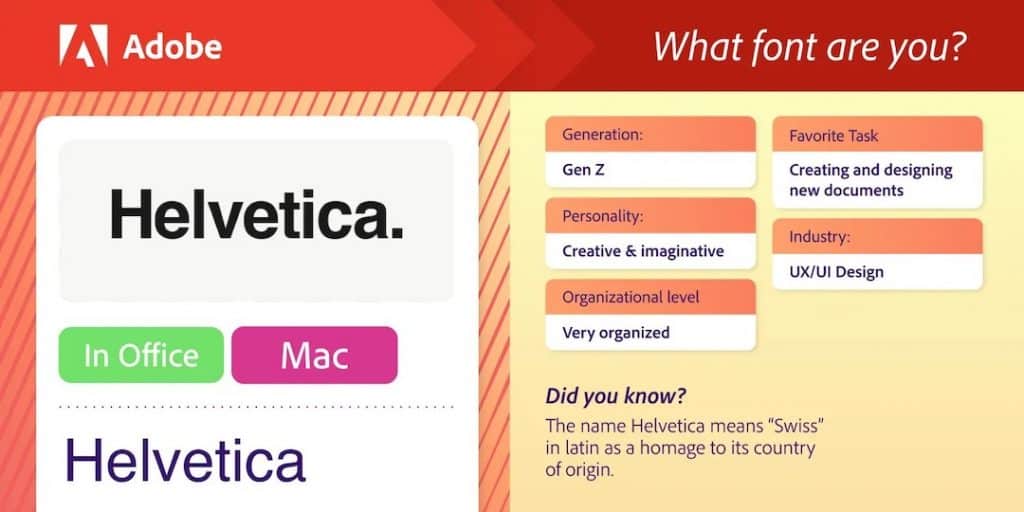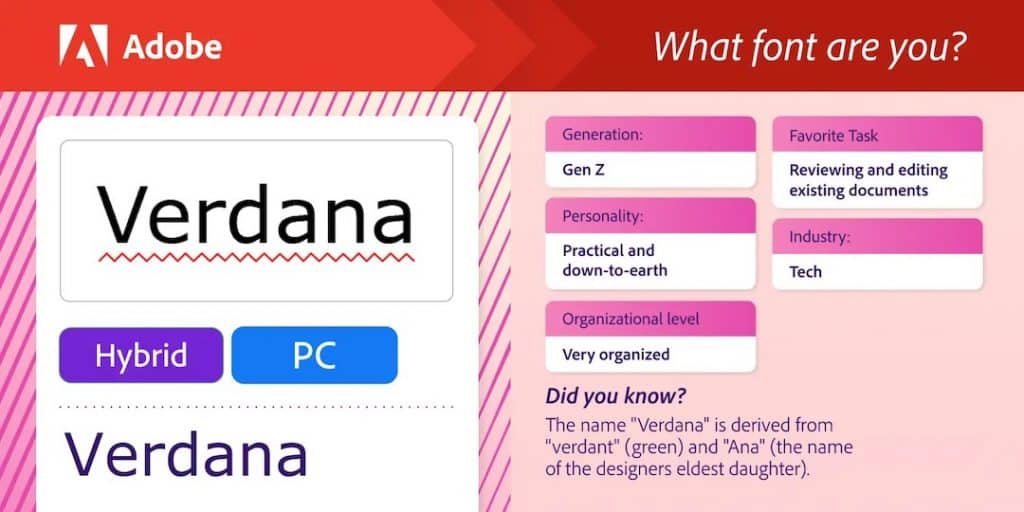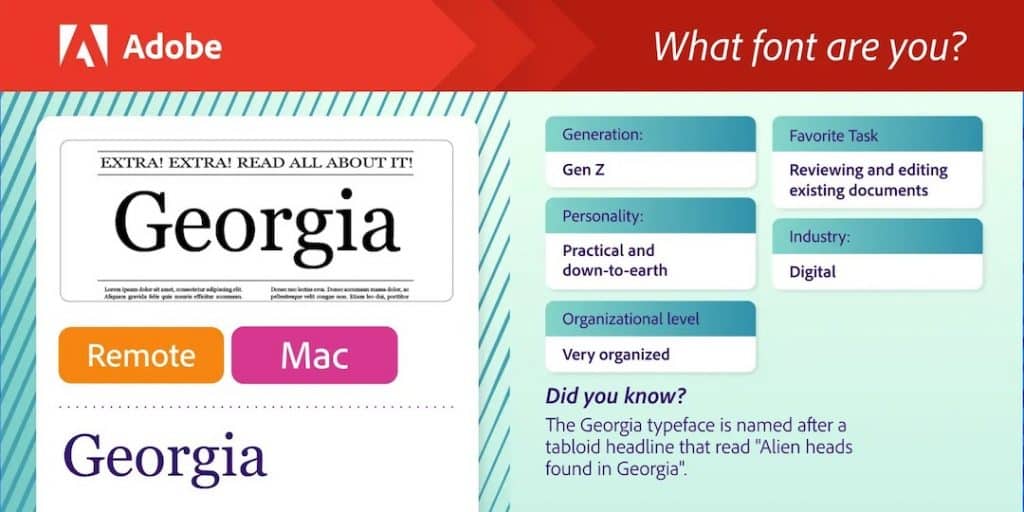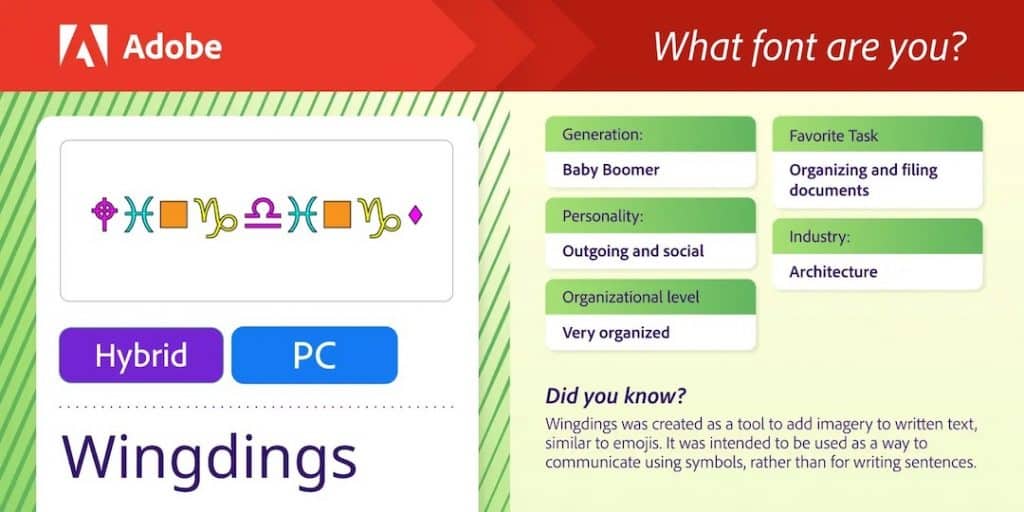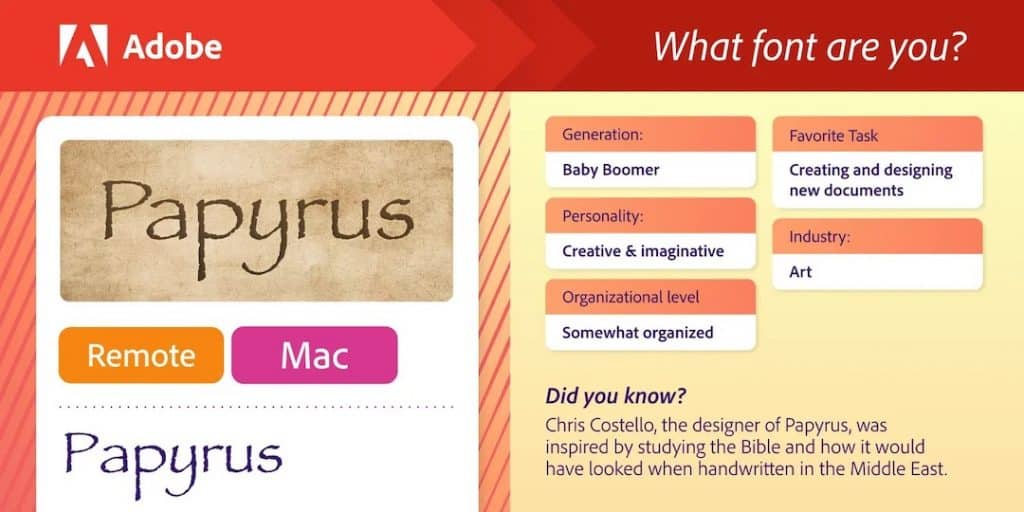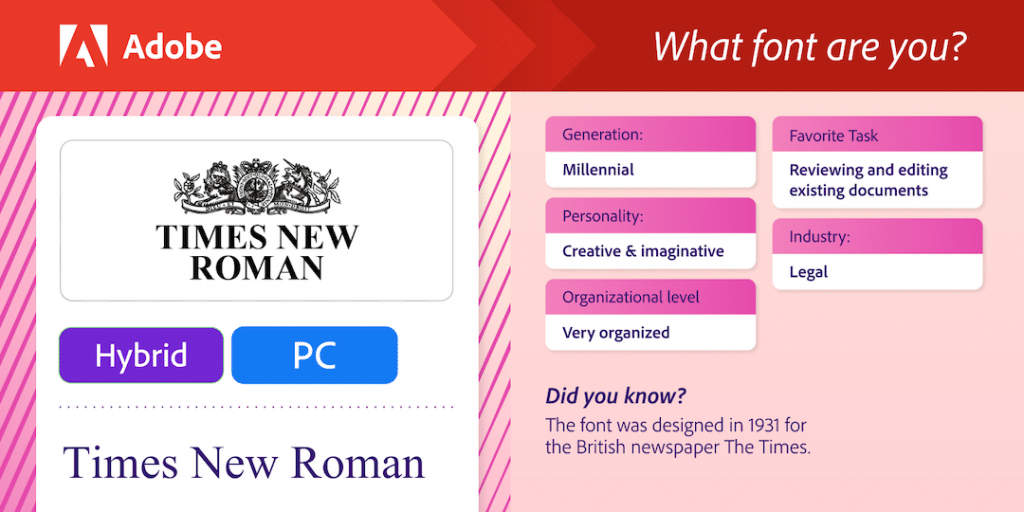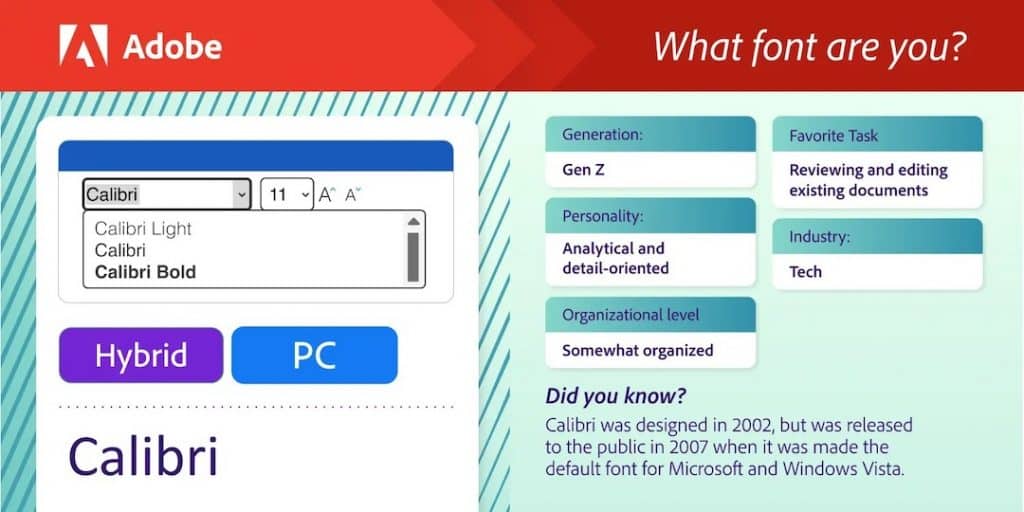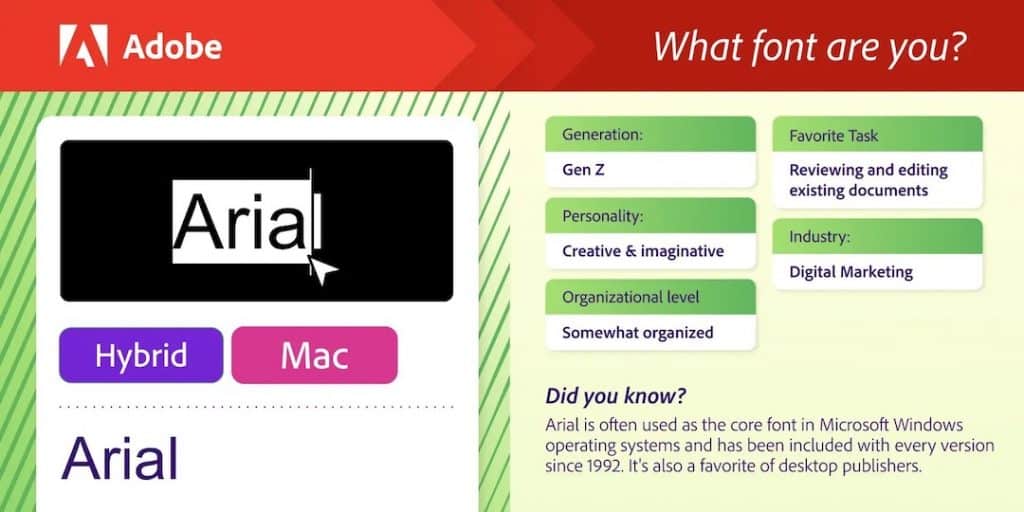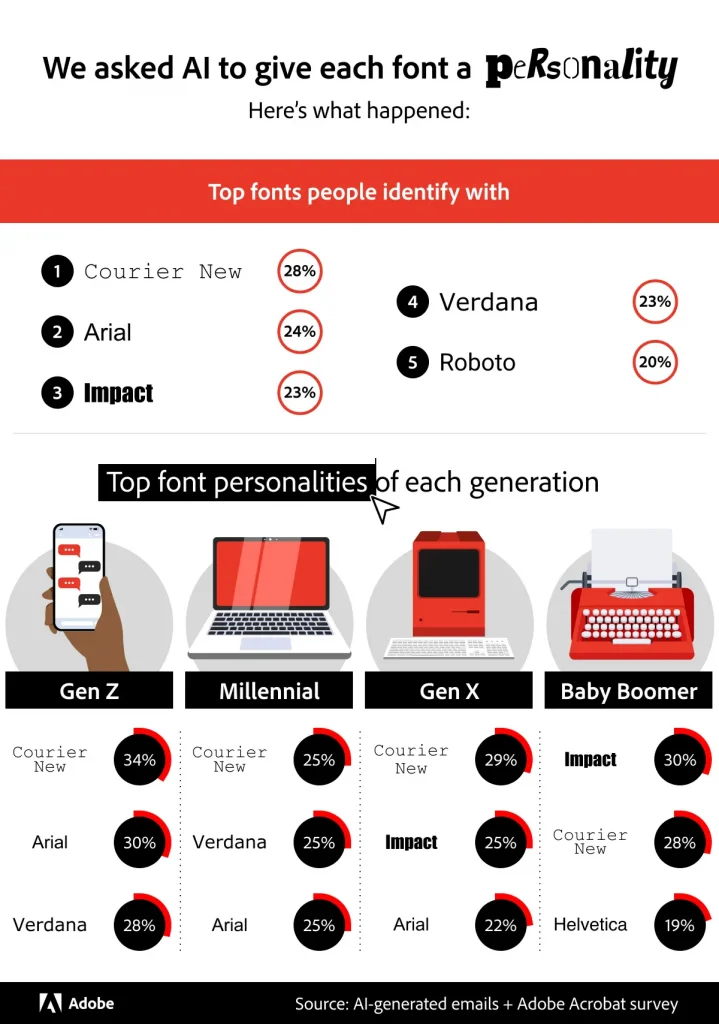
Bạn là một serif táo bạo, mới lạ hay luôn nằm gọn trong những đường thẳng ngay ngắn? Adobe Acrobat vừa công bố 13 phông chữ biểu trưng cho các kiểu tính cách, mời gọi những người yêu thích phông chữ khám phá “người bạn đồng điệu” của mình.
Trong khi nhiều người vẫn hình dung được những phông chữ khác nhau có thể truyền tải tính cách ra sao, Adobe đã tiến thêm một bước khi sử dụng trí tuệ nhân tạo để định hình các tính cách riêng biệt. Adobe khởi đầu bằng cách sử dụng AI để tạo ra 13 mẫu email cá nhân hoá dựa trên những phông chữ phổ biến như Helvetica, Times New Roman hay Comic Sans, sau đó khảo sát với hơn 1.000 người Mỹ để tìm hiểu mức độ tương đồng của mỗi tính cách với các phông chữ này.
Kết quả cho thấy, Courier New là phông chữ dễ tạo cảm giác gần gũi nhất, thu hút hơn một phần tư người tham gia nhờ phong cách giản dị và chân thật.
Trong khi đó, Comic Sans – một trong những phông chữ gây tranh cãi nhất trên internet – được miêu tả là nhiệt tình và khích lệ, còn Helvetica có một phong thái súc tích và mang tính thông tin. Còn Wingdings? Nếu có tính cách, nhiều người cho rằng nó sẽ phù hợp với ngành kiến trúc và rất hướng ngoại.
Ở các thế hệ khác nhau, Courier New vẫn duy trì được sức hút, dẫn đầu ở hầu hết các nhóm, ngoại trừ thế hệ baby boomers – họ thấy Impact là phông chữ dễ gợi sự tương đồng nhất. Về phần Times New Roman, phông chữ này không được ưa chuộng như kỳ vọng, chỉ đứng thứ tám trong danh sách các phong cách mà mọi người muốn sử dụng trong email. Kết quả này dường như đang thử thách vị trí “kinh điển” của Times New Roman trong lĩnh vực giao tiếp trang trọng.
“Cũng giống như các cung hoàng đạo tiết lộ phần nào về tính cách, những phông chữ này cũng có thể cho bạn biết về ‘tâm hồn’ của mình qua những ‘font hoàng đạo’ thú vị, từ sự sáng tạo của Lobster đến tính thực tế của Arial. Hãy để những phông chữ này dẫn lối và giúp bạn tự tin lựa chọn bản sắc số phù hợp với mình,” Adobe Acrobat chia sẻ. Cho dù bạn yêu thích sự tinh giản của Helvetica hay năng lượng “vui nhộn” của Comic Sans, đây là một cách thú vị để nhìn nhận phông chữ như một phần nào đó phản ánh tính cách cá nhân.
Font Helvetica
Font Times New Roman
Font Calibri
Font Arial
Font Impact
Font Comic Sans
Font Roboto
Font Lobster
Font Courier New
Font Verdana
Font Georgia
Font Wingdings
Font Papyrus
Không chần chừ gì nữa, hãy khám phá “người bạn phông chữ” của bạn ngay nhé!